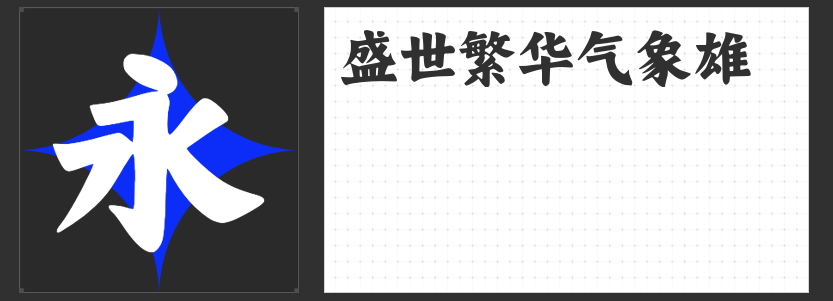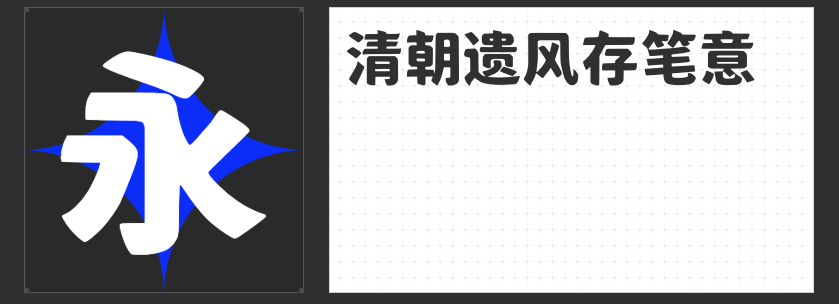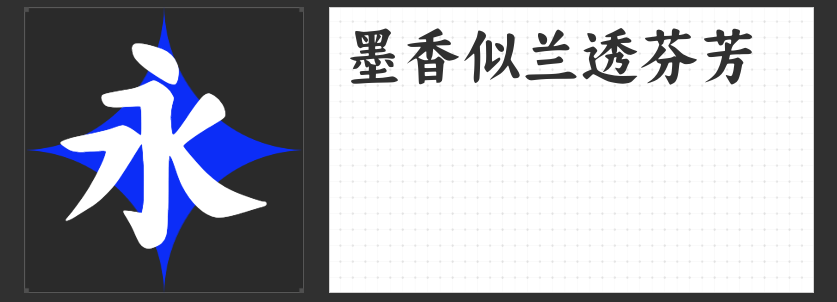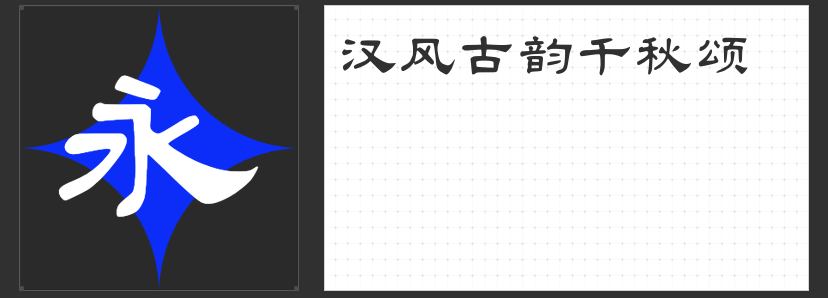
字库字体推荐:四款古风设计字体,让设计作品焕发历史韵味
在设计中,字体的选择往往决定了作品的整体风格和氛围。今天,为大家推荐四款古风设计字体,它们不仅承载着历史的厚重,更能在现代设计中绽放异彩。
首先,让我们来看看“大萌唐”。这款微胖楷体以盛唐气象为灵感,字体圆润饱满,笔触间流露出大唐盛世的繁荣与自信。使用“大萌唐”进行设计,仿佛能让人穿越时空,回到那个辉煌的时代。它的每一笔每一划都充满了力量感,让观者在字里行间感受到那份跨越千年的辉煌与魅力。无论是海报设计、书籍封面还是包装设计,“大萌唐”都能为你的作品增添一份独特的历史韵味。
接下来是“大萌宋”。这款温润仿宋字体不仅承载着历史的厚重,更在现代设计的舞台上展现出了独特的魅力。它的温润质感仿佛能穿越时空,将古人的风雅与现代审美巧妙融合。使用“大萌宋”进行设计,可以让你的作品在保持现代感的同时,又不失传统文化的底蕴。无论是网页设计、广告文案还是品牌标识,“大萌宋”都能为你的作品增添一份古朴与雅致。
再来看看“大萌清”。这款清朝民国体在宣纸轻展的柔光里,与民国风韵交织成一幅跨越时空的画卷。它的字体风格独特,既有清朝的端庄与大气,又不失民国的柔美与细腻。使用“大萌清”进行设计,可以让你的作品在保持传统美感的同时,又融入了一丝现代元素。无论是邀请函设计、名片制作还是宣传册排版,“大萌清”都能为你的作品增添一份独特的韵味。
最后是“大萌汉”。这款以古隶体为基础设计的古风字体,在加入现代设计元素后,更加端庄与雅致。它的字体结构清晰明了,线条流畅自然,让人在欣赏的同时也能感受到传统文化的魅力。使用“大萌汉”进行设计,可以让你的作品在保持古风韵味的同时,又不失现代感与时尚感。无论是书法展览、文化宣传还是艺术创作,“大萌汉”都能为你的作品增添一份独特的文化气息。
以上就是为大家推荐的四款古风设计字体。它们不仅各具特色,而且都能在现代设计中发挥出独特的魅力。希望这些字体能为你的设计作品增添一份历史韵味与文化底蕴。